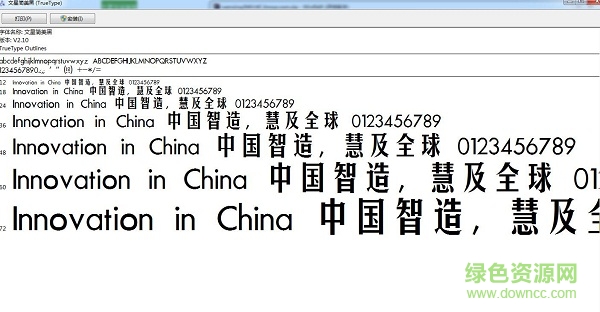
軟件介紹 軟件標簽: 文星字體 美黑字體 文星簡美黑字體是一款結(jié)構(gòu)簡潔的中文黑體字體,字形挺拔瘦長,線條勾勒清楚,適合用在廣告設(shè)計、宣傳海報、兒童讀物等方面,喜歡的朋友快來免費下載吧!個性字體推薦【雪峰體】 美術(shù)體字;每個字頂上如白雪覆蓋,高低錯落,似山頂上的雪峰 hyo2gj 授權(quán):免費軟件 WinAll, WinXP, Win7, Win8, Win10大?。?.7M語言:中文hyo2gj字體就是漢儀雪峰體,這款字體外形就像雪峰一樣,字體風格非常獨特,很受設(shè)計師們的喜愛!需要的朋友歡迎來綠色資源網(wǎng)下載安裝。字體介紹hyo2gj是像雪峰一樣的個性字體,字體筆畫較粗,上白下黑,用在廣告設(shè)計下載地址【竹節(jié)體】風格獨特,筆畫似大自然中的竹節(jié)形態(tài),粗壯有力,蒼勁挺拔hyq1gj-常規(guī)體 授權(quán):免費軟件 WinAll, WinXP, Win7, Win8大?。?.7M語言:中文hyq1gj字體的中文名稱為漢儀竹節(jié)體,這款字體一節(jié)節(jié)的,形似竹子,構(gòu)思新穎,廣告效果出色,非常有個性,喜歡的小伙伴歡迎免費下載使用!特色漢儀字體介紹漢儀花蝶體:筆畫修長、字形秀美、飄逸灑脫。漢儀哈哈體:為下載地址文星簡美黑字體安裝說明方法一:控制面板/字體/文件/安裝新字體;方法二:直接將字體復制到C:\WINDOWS\Fonts。方法三:針對win7系統(tǒng),用戶只需選中字體右鍵安裝即可。 軟件截圖 上一張下一張(1 / 1) 安裝詳細截圖 其他版本下載 標題 大小 更新日期 下載 下載地址 電腦版 文星簡美黑 點擊報錯 軟件無法下載或下載后無法使用,請點擊報錯,謝謝! 關(guān)閉報錯反饋 請描述您所遇到的錯誤,我們將盡快予以修正,謝謝! *必填項,請輸入內(nèi)容 本類最新 dreamweaver字體庫 首爾南山體字體 v1.06 官方版 潮字社風云簡ttf 潮字社凌渡鯤鵬簡體字體 潮字社曾玉波手書簡字體 微博慧心字體 用戶評論 熱門評論 最新評論 發(fā)表評論 查看所有評論(0) 昵稱: 請不要評論無意義或臟話,我們所有評論會有人工審核. 字數(shù): 0/500 (您的評論需要經(jīng)過審核才能顯示)